36 лучших курсивных шрифтов 2023 года (бесплатно и премиум)
Опубликовано: 2023-04-30Вы устали от использования одних и тех же старых шрифтов по умолчанию для своих проектов и документов? Хотите добавить нотку элегантности и изысканности в свою работу? Посмотрите не дальше нашего списка 36 лучших курсивных шрифтов!
В этой статье мы покажем лучшие курсивные шрифты, которые помогут вывести ваш дизайн на новый уровень. От классической каллиграфии до современного письма кистью — эти шрифты идеально подходят для свадебных приглашений, логотипов, графики для социальных сетей и многого другого.
Знаете ли вы, что использование уникального шрифта может увеличить вероятность того, что кто-то запомнит ваш бренд или сообщение, на 80%? С нашим тщательно подобранным списком вы сможете выделиться из толпы и произвести неизгладимое впечатление.
Итак, являетесь ли вы дизайнером, маркетологом или просто любителем красивой типографики, читайте дальше, чтобы узнать о лучших курсивных шрифтах для вашего следующего проекта.
Лучшие курсивные шрифты премиум-класса
В этой статье мы продемонстрируем некоторые из лучших курсивных шрифтов премиум-класса на рынке, подробно описав их уникальные особенности и выделив то, что отличает их от остальных. Поиск идеального курсивного шрифта может быть непростой задачей, но с нашим полным списком мы надеемся облегчить вам поиск идеального шрифта для вашего следующего проекта.
Алиша
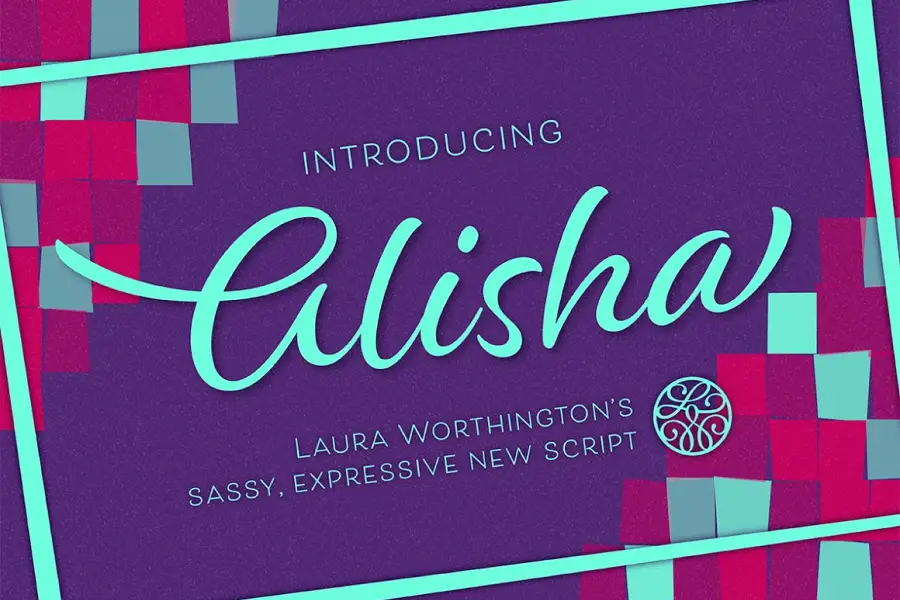
Alisha — это красиво оформленный рукописный шрифт, который сочетает в себе элегантность и разборчивость. Этот шрифт с более чем 200 альтернативами и формами перекоса идеально подходит для добавления человеческого прикосновения к любому проекту или дизайну.
Разнообразные формы букв в Alisha создают ощущение рукописного письма, сохраняя при этом отточенный и изысканный вид. Его большая высота по оси x позволяет легко читать его в небольших размерах, что делает его идеальным для упаковки продуктов или заголовков.
Уникальный стиль Алиши также можно использовать для создания впечатляющих фирменных знаков и словесных знаков, которые одинаково очаруют как клиентов, так и заказчиков. Это идеальный шрифт для тех, кто хочет добавить индивидуальности своему дизайну, не жертвуя при этом профессионализмом.
Сожженная роза
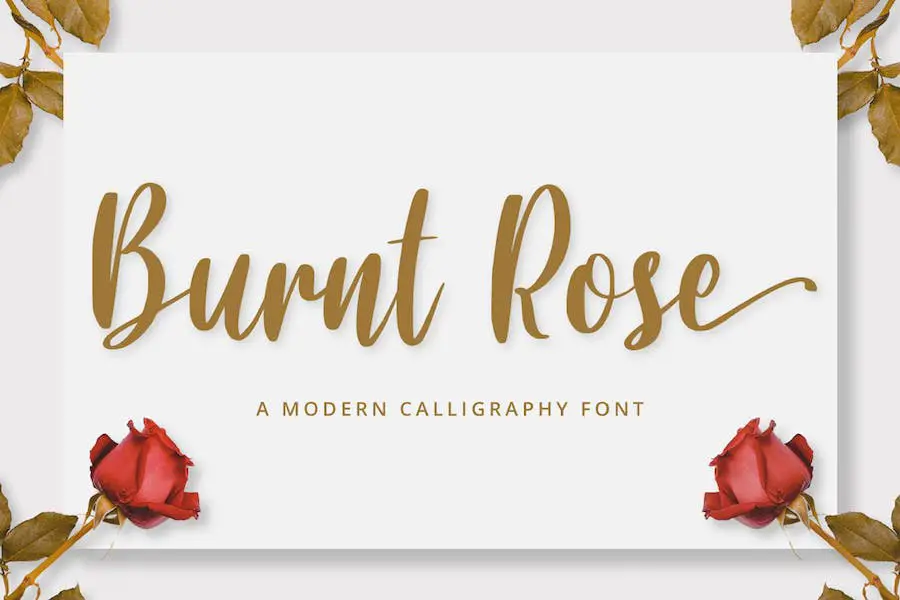
Burnt Rose — это современный каллиграфический шрифт, который добавляет элегантности и стиля вашим проектам брендинга, дизайну веб-сайтов и печатным материалам. Этот шрифт ручной работы отражает суть изысканного дизайна в каждом штрихе и изгибе.
С помощью Burnt Rose вы можете произвести впечатление на свою аудиторию с помощью наборов лигатур и стилей и многоязычной поддержки, что делает его глобально приемлемым для любого проекта по брендингу. Он идеально подходит для баннеров, постов и рекламы в социальных сетях, а также для печатных цитат, дизайнов футболок, упаковки или даже в качестве наложения текста на любое фоновое изображение.
Багет Сценарий
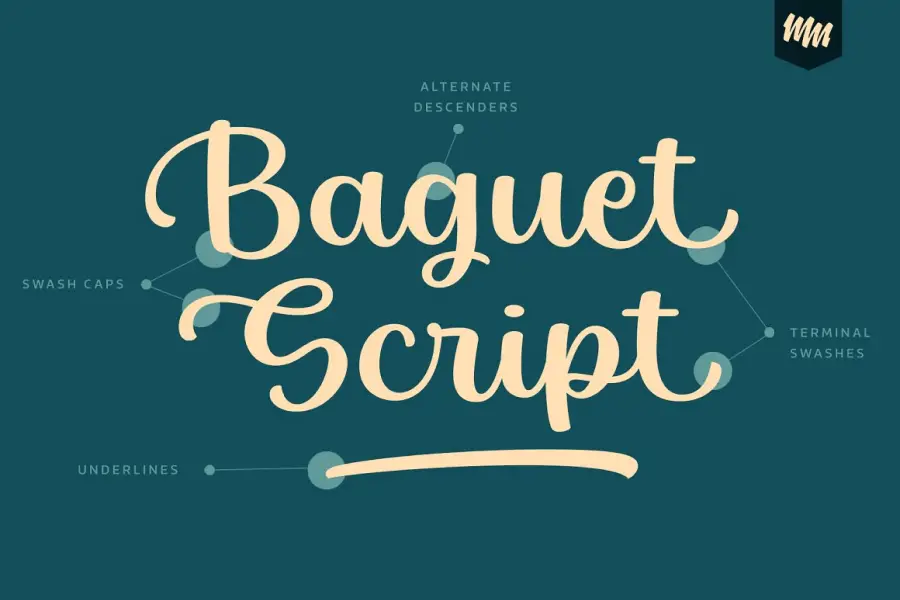
Baguet Script — это универсальный и современный шрифт с кистью, который предлагает ряд опций и функций. Буквы имеют мягкие терминалы и небольшой отскок и состоят из двух наборов прописных букв: один простой, а другой более яркий.
Этот курсивный шрифт также включает в себя три различных типа совпадающих начальных и конечных штрихов для строчных букв, а также несколько вариантов для надстрочных и подстрочных элементов. Эти дополнительные функции упрощают создание уникальных и персонализированных дизайнов.
В целом, если вы ищете мягкий, удобный и современный рукописный шрифт с множеством опций и универсальностью, вам определенно стоит попробовать Baguet Script. Он идеально подходит для создания всего: от приглашений до логотипов и графики для социальных сетей.
Кениленд
Quenyland — это великолепный рукописный шрифт, который добавит элегантности любому дизайн-проекту. Его стиль каллиграфии делает его идеальным для украшения пригласительных билетов, материалов для брендинга, визитных карточек, цитат, плакатов и всего остального, что требует особого внимания.
Что отличает Quenyland от других шрифтов, так это разнообразие доступных альтернативных символов. С такими параметрами, как стилистические наборы, стилистические альтернативы, контекстная альтернатива, SWASH и лигатура, вы можете настроить текст в соответствии со своими конкретными потребностями.
Доступ к этим функциям легко получить с помощью программ Open Type, таких как Adobe Illustrator, Adobe InDesign, версия Adobe Photoshop Corel Draw X и Microsoft Word.
Лука Ноа
Luca Noah — потрясающий шрифт с сердечками, который идеально подходит для создания романтичных и женственных дизайнов. Этот шрифт идеально подходит для свадебных приглашений, карточек с датой, художественной бумаги, личных подарочных карт и других романтических проектов.
Одной из выдающихся особенностей Luca Noah является дизайн шрифта в форме сердца, который добавляет элегантности и изысканности любому проекту. Плавные изгибы шрифта и нежные штрихи создают ощущение тепла и интимности, что делает его отличным выбором для интимных мероприятий.